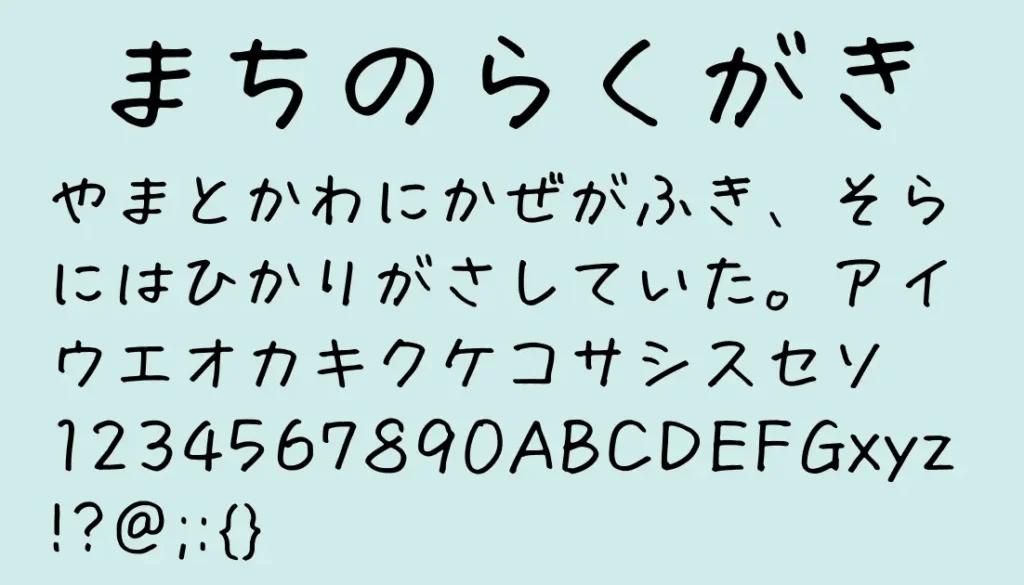
ゆるくラフな線で書かれた、落書き感覚の手書きフォント。整いすぎない字形がやさしい空気感を作り、日記風デザインやSNS画像、カジュアルなタイトルにぴったりです。肩の力が抜けた雰囲気が魅力で、堅い印象を避けたい場面におすすめ。ひらがな中心のやわらかな表現を活かし、親しみやすいビジュアルづくりに活躍します。
まちのらくがき